フォントを作る人に聞いてみた その7:最初にデザインするグリフ
タイププロジェクトのデザイナー達に「書体デザインをするときに最初に作るグリフ」は何かを聞いてみました。
和文デザイナーの回答の中で特定のグリフとして多く挙げられたのは「あ」でした。 また、その次に多かったのが「書体の雰囲気にあったグリフ」という回答です。 やはり最初に作る文字はその後に続く文字のデザインの基準にもなるので、書体全体のイメージを想像しやすいグリフから作業を始める人が多いのではないでしょうか。
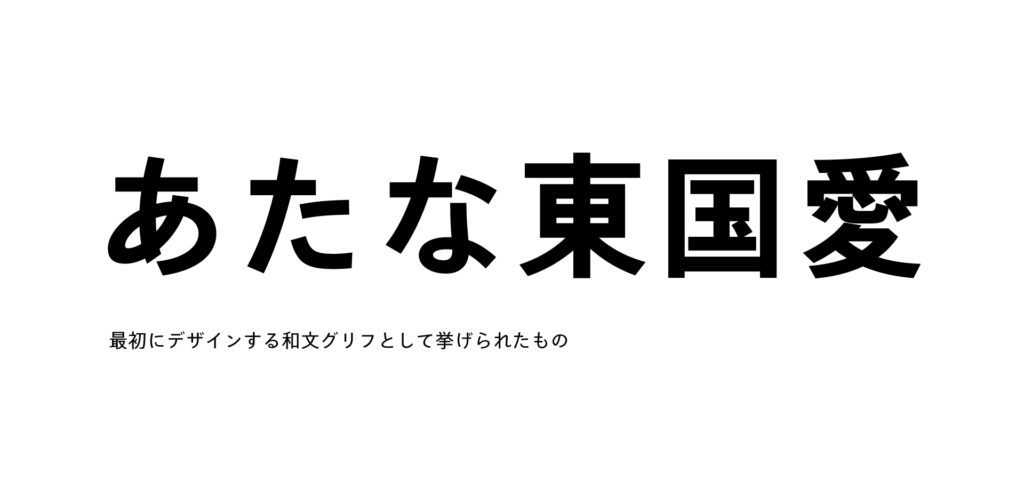
- 「あ」、もしくはその書体に合った言葉に使う文字:
「あ」はその書体のもつ雰囲気を考えるのに一番最初に書いてしまいます。
- 「東、国、愛」「あ、た、な」:
あまり制作経験数はありませんが、ひらがなか漢字から作っています。
- 書体によって変わりますが、早い段階で作ることが多いのは「あ」:
書体によっては漢字から入る場合も少なくありません。
- 資料に必要な文字・その書体っぽい単語:
タイププロジェクトの作業では資料に必要な文字からです。個人で作るときはその書体っぽい単語からが多いです。それで雰囲気が出るとモチベーションが上がります。
- まずイメージにあった単語を決めて始めるので、特に決まってないです。
欧文デザイナーの回答には「adhesion」が共通して出てきました。
欧文デザインのワークショップや授業などで推奨されることの多いこの8字は、その他のグリフに応用できる要素がバランス良く含まれている文字列です。 欧文制作中のデザインチェック用に使用するテキストを生成できる「adhesiontext」というウェブサイトもあります。
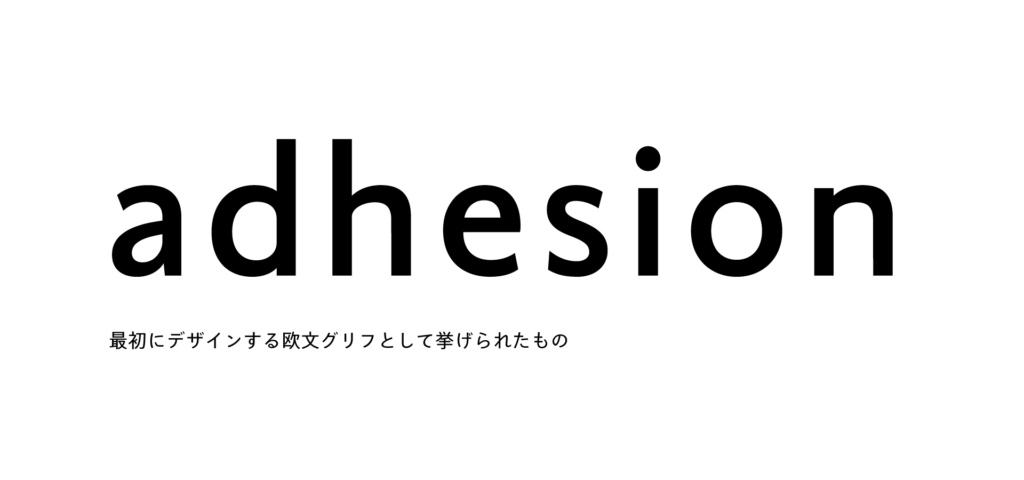
- a, n, d:
大学時代の授業で「adhesion」から作ると良いと習って以降それらの文字から始めていますが、さっとスケッチなどをする際に8文字は多いので、特に書体の特徴を表しやすい「a」その他のグリフに応用しやすいエレメントのある「n」「d」の3文字から入ることが多いです。
- a:
欧文でAdhesion という作り始めの文を私は間違えてadhesion でつくってしまっていて、それが長年の癖になってしまった.